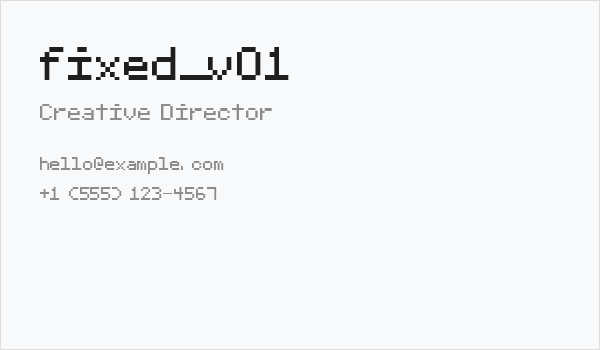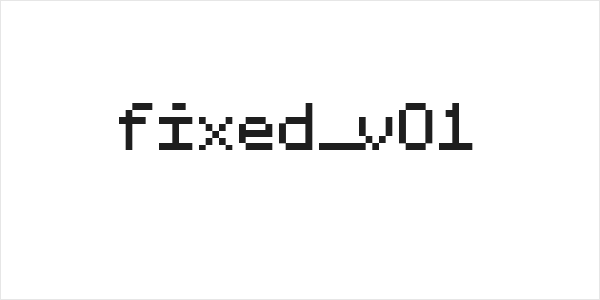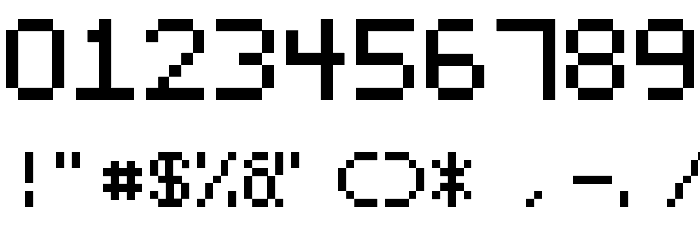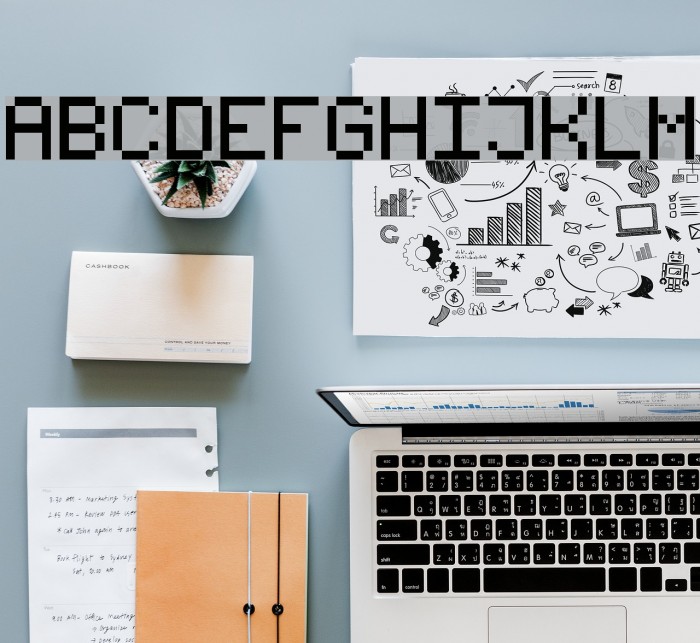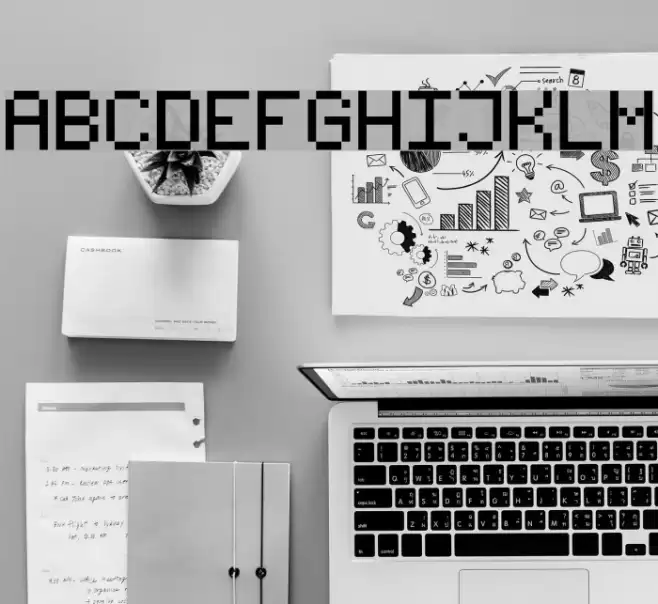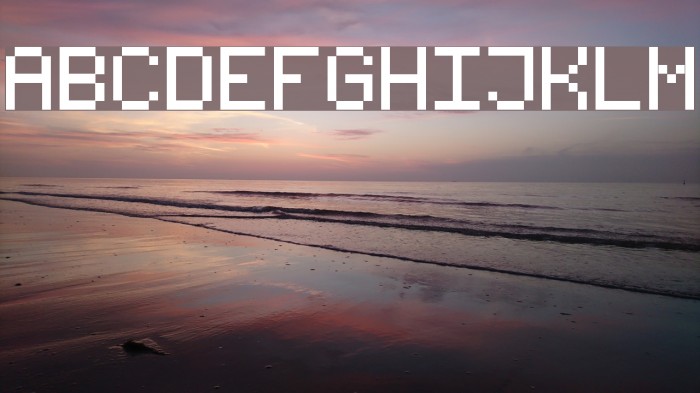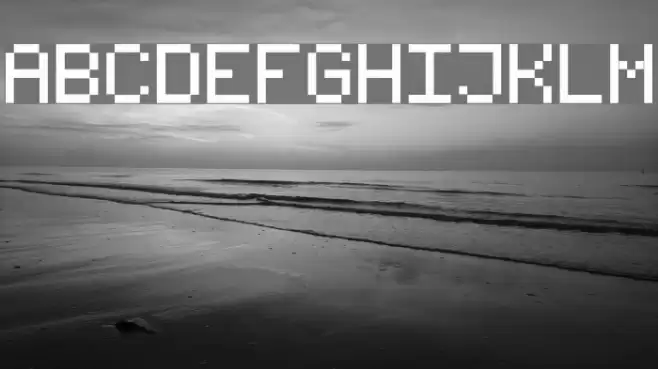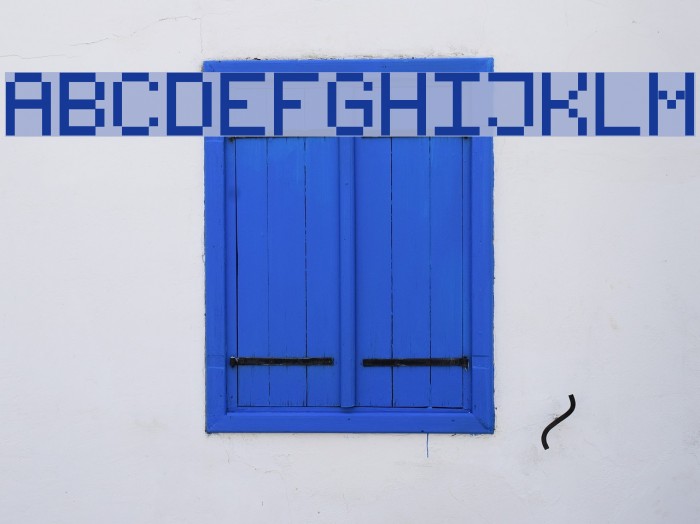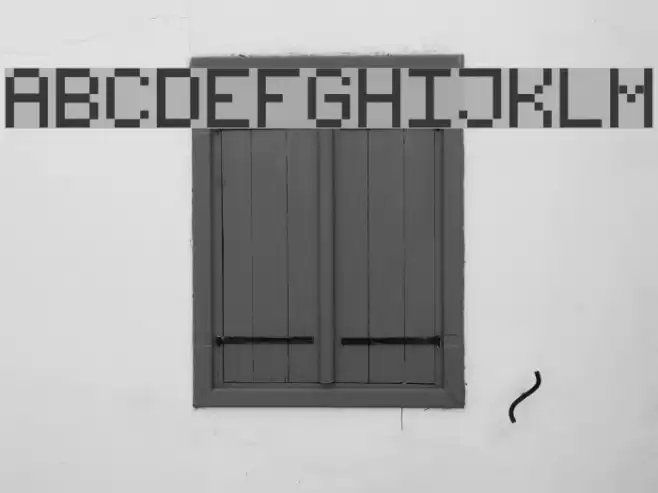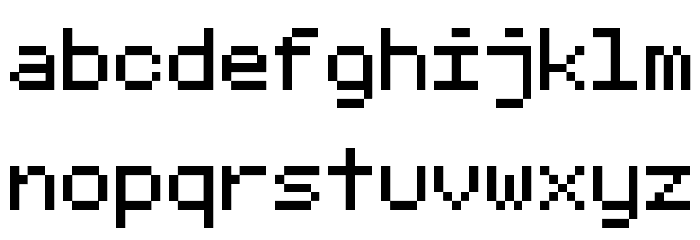
fixed_v01 Font
| Estilo general | Vintage |
| Caso de uso | Logos, Headlines, Digital displays |
| Proyectos propuestos | Ideal for retro video game designs, digital art projects, tech-themed posters, and any creative work that requires a nostalgic digital aesthetic. |